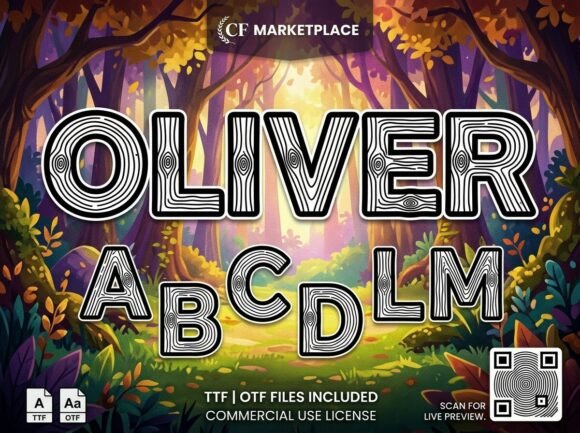
Oliver
Si buscas recursos de alta calidad como Oliver, este paquete premium es una opción fantástica para tus proyectos creativos.
Ya sea que estés creando productos POD (impresión bajo demanda), invitaciones de boda o gráficos para redes sociales, Oliver es una opción ideal.